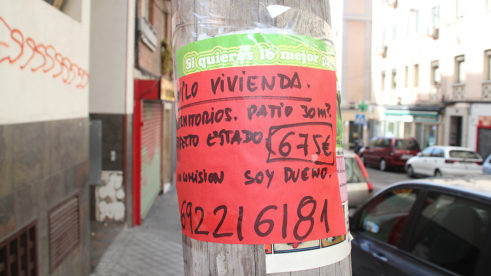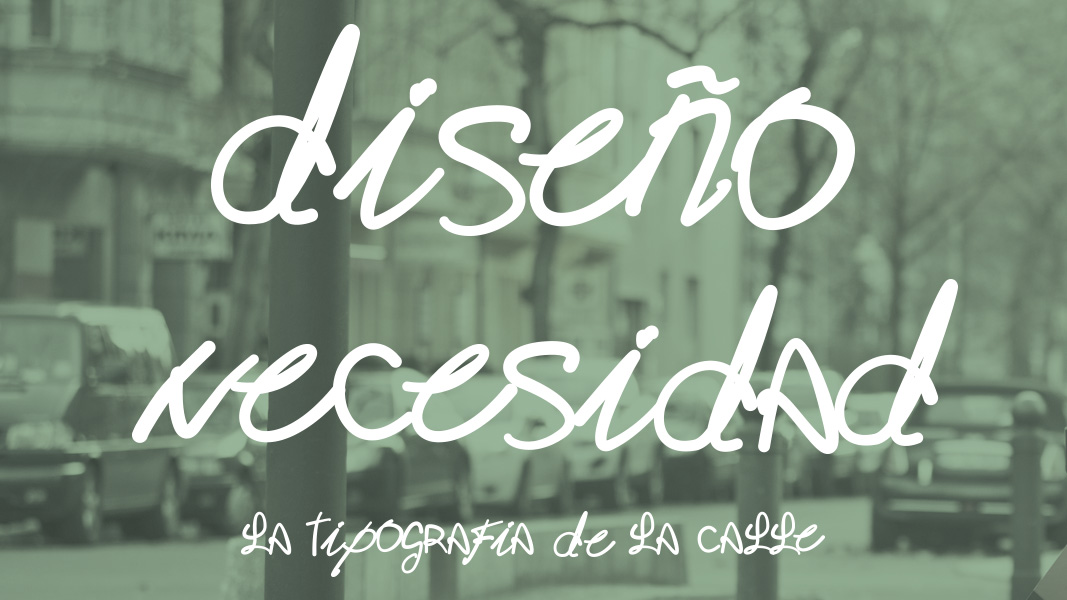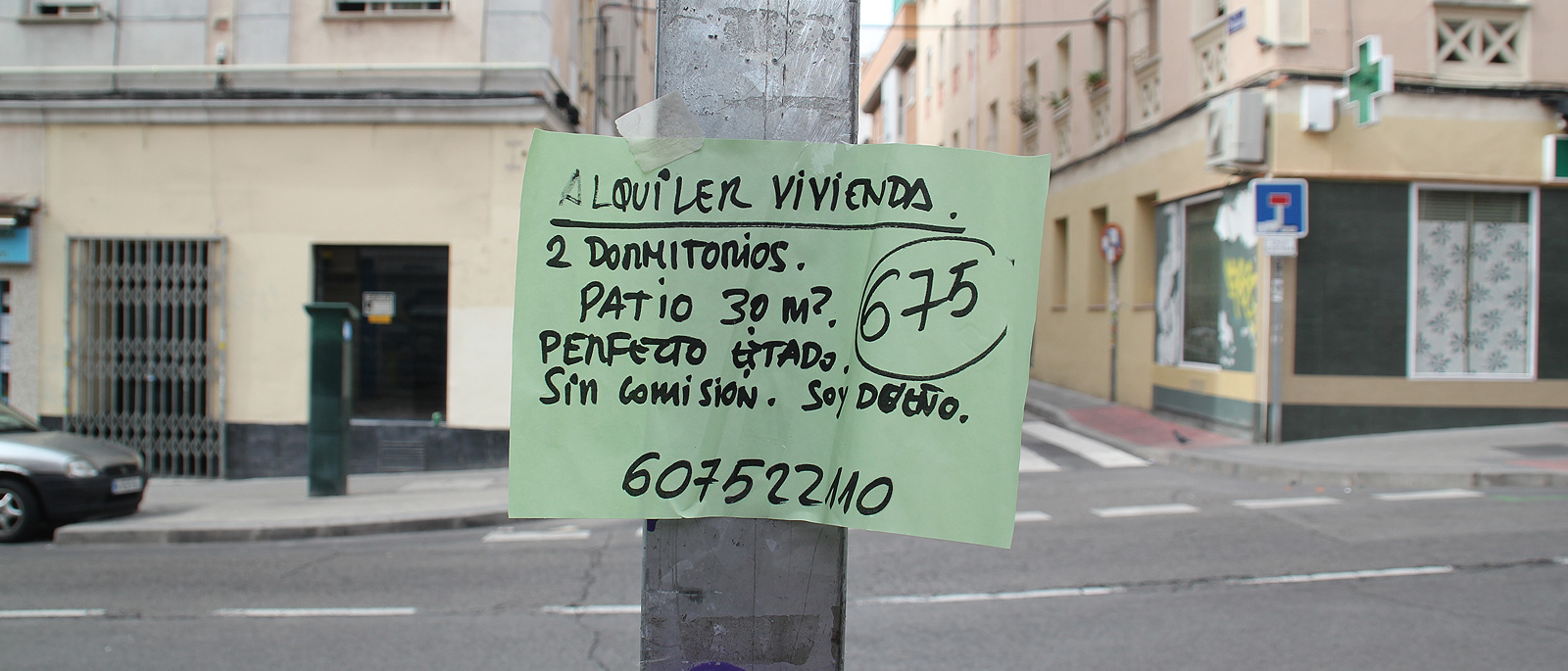
Diseño por necesidad, la tipografía de la calle
En nuestro día a día solemos ignorar los anuncios manuscritos que se encuentran sobre cualquier superficie de nuestro barrio pegados con celo, sacados de papel de libreta, hechos con rotuladores y fotocopiados en mayor o menor número. Esos mensajes son del estilo «se ofrece chica para limpiar», «se alquila habitación», «compro piso en esta zona»...
Son mensajes que estamos tan acostumbrados a ver que ni nos merece la pena que nos paremos a leerlos. Sin embargo, el estudio madrileño Grantipo, especializado en branding y packaging, convirtió las caligrafías usadas en estos anuncios en las protagonistas de un proyecto tipográfico. Aprovecharon estos escritos a mano con prisa y por necesidad para convertirlas en una fuente, cuyos caracteres fueron creados a partir de esos textos manuscritos.
Al proyecto lo llamaron Diseño por Necesidad y lo empezaron a desarrollar en 2012 para homenajear a esos textos cotidianos tan frecuentes en las calles de cualquier ciudad: ese «diseño» que no piensa en ser diseño, sino que simplemente busca comunicar un mensaje de la forma más económica, directa y eficaz. De esta manera, Grantipo quería darles un hogar a todas esas letras abandonadas en las calles de cualquier localidad.
El resultado final fue la tipo a la que llamaron «la tipografía de la calle», y cuyos caracteres están extraídos de 50 mensajes que lo único que tienen en común es que han sido encontrados en un anuncio manuscrito en una vía pública. Una tipografía que puede ser imperfecta desde el punto de vista técnico, pero que está dotada de gran humanidad.